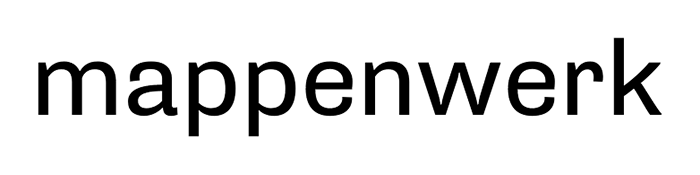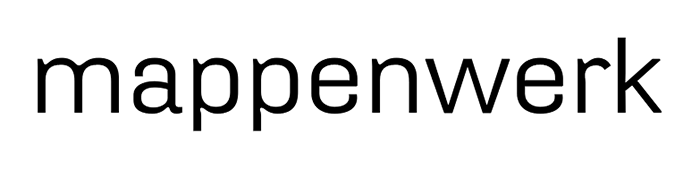
Stencil-Font Römerturm Mappenwerk
ich gehe davon aus, dass der stencil-effekt selbst gemacht ist. als basis scheint mir die supria sans gedient zu haben:
abgesehen von den löchern haben sie offensichtlich auch noch das ›r‹ gestutzt.
klasse, vielen Dank! das kam mir auch schon in den sinn, dass da selbst etwas gebastelt wurde aber ich kam auch nicht auf die mögliche ausgangsschrift
der schwung aus dem k ist auch weg
Mir fallen die rechteckig ausgespannten Formen auf. Sehr schön zu erkennen beim e und p, selbst beim a. Ist das die Folge der Stanzenherstellung oder diente womöglich doch ein anderer Font als Vorlage? :-? Die Supria ist auf alle Fälle schon nah dran, aber ich habe den dumpfen Verdacht, dass es da noch eine andere gibt … aber ich komme im Moment auch nicht drauf.
ich weiß auch nicht genug von der technik, mit der die schrift da aufgebracht wurde, um sagen zu können, ob die unterschiede zwischen font und abbildung daher kommen, dass die vorlage eine andere war, oder daher, dass sich bei der umsetzung die eine oder andere ungenauigkeit ergibt (bzw. feinheiten aus der vorlage eliminiert wurden, weil sie nur schwer oder gar nicht wiederzugeben wären). in manchen punkten, zum beispiel beim ›e‹ oder beim ›a‹ (abgesehen von der oberkante des auges), deckt sich die supria sans jedenfalls ziemlich exakt mit deiner abbildung – so exakt, dass ich vermute, dass die unterschiede dann doch in der herstellung oder dem leicht verzerrenden foto zu suchen sind.
Thierry hat recht, es wurde die Hydra Text Regular verwendet.